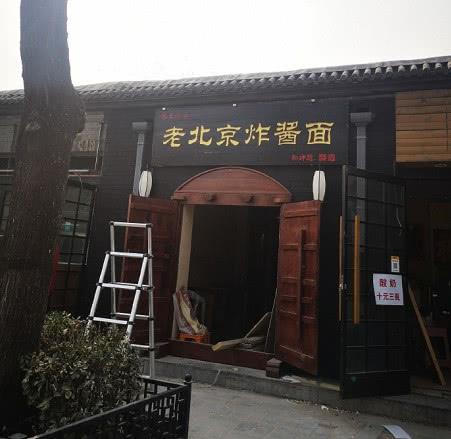
电脑字体写了“老北京炸酱面”六个字,落款却是清代大臣和珅
北京一家炸酱面馆3月18日刚挂上牌匾,就马上成了“网红”。原来,这家面馆的牌匾上用电脑字体写了“老北京炸酱面”六个字,落款却是清代大臣和珅。有趣的是,这几个字还要用电脑字体,令人啼笑皆非。在网友们的热议中,该牌匾当天下午就被摘除。
没猜错的话,这应该是华文隶书吧
《北京日报》报道称,这家“老北京炸酱面”的牌匾相当辣眼睛,不但滥用“老北京”冒充老字号让人反感,而且还拉来古人和珅“代言”;明明是类似“华文隶书”的电脑字体,却在后面写了个“和珅题”,让人哭笑不得的是,这三个字也是电脑字体。